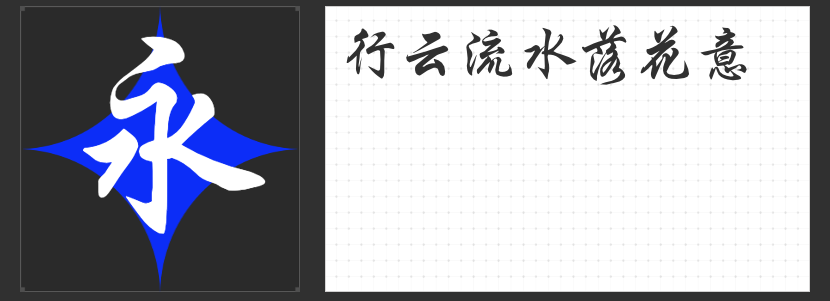
四款新中式字体,书写东方美学新章
新中式设计浪潮中,字体作为文化符号的载体,既要传承传统书法的气韵,又要契合现代审美。以下四款字体以笔墨当随时代的创新精神,为设计师提供兼具文化底蕴与视觉张力的解决方案。
一、造字侠磅礴简繁
此字体以中锋运笔构建骨架,笔画粗细对比强烈,飞白处若宣纸留痕。转折处方圆并济,既有楷书之正,又具行书之活。在茶室品牌或山水画卷展签设计中,其"一波三折"的运笔节奏能唤起观者对水墨山水的想象,尤其适合表现"气吞云梦"的壮阔意境。
二、励字行草简繁
介于行草之间的这款字体,完美平衡了识别性与艺术性。其线条如松烟墨色在生宣上晕染,连笔处似断还连,既保留行书章法又注入草书灵性。在文创笔记本封面或古籍再版设计中,既能承载经典文本,又能展现"笔墨当随时代"的创新精神。
三、励字行楷简繁
这款字体取法"二王"笔意,点画呼应如琴瑟和鸣。其结构在楷法严谨中见行草逸趣,横画略向右上取势,竖画挺拔如松。适用于新中式家居产品目录或文化讲座海报,能在现代排版中保留"不激不厉,风规自远"的传统韵致。
四、造字侠仗剑简繁
这款字体以碑刻入笔,折、提、钩等部首如剑锋出鞘。笔画高度凝练,转折处多见方笔,字间留白若剑气游走。在武侠游戏LOGO或非遗武术展陈中,其"铁画银钩"的笔势能传递"十步杀一人,千里不留行"的豪气,是数字时代的刀光剑影。
四款字体构建了从新古典到现代文创的完整设计语言体系:磅礴体适合营造空间意境,行草体传递文化温度,行楷体塑造书卷气质,仗剑体注入江湖侠气。当传统书法智慧与现代设计思维相遇,字体便成为连接过去与未来的文化桥梁,让东方美学在数字时代绽放新姿。